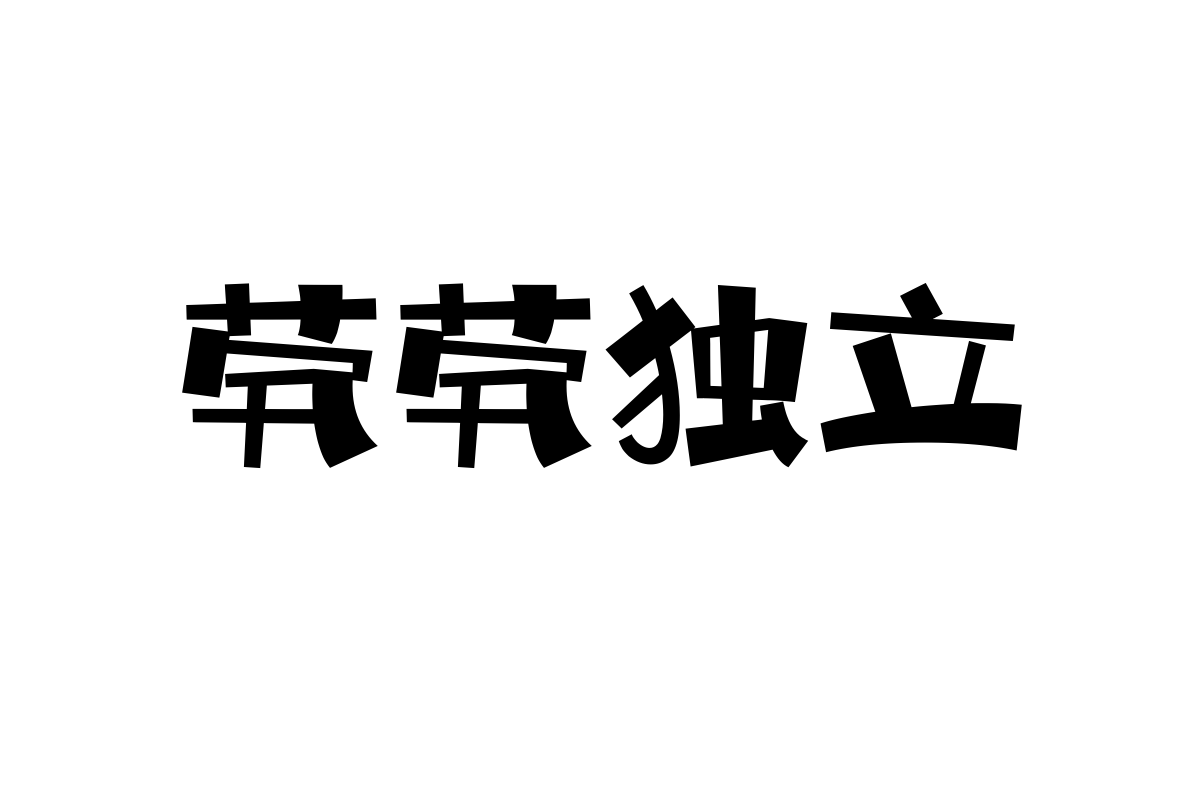
麦兜体是一种字体,它的字形独特,笔画流畅,给人一种轻松愉快的感觉。这种字体的特点是将麦兜这个角色的形象融入到了文字设计中,使得文字既有趣味性又不失正式感。
麦兜体的特点主要有以下几点:
1. 字形独特:麦兜体的字形不同于传统的宋体、黑体等标准字体,它有着独特的线条和形状,给人一种新颖的感觉。
2. 笔画流畅:麦兜体的笔画流畅,没有太多的停顿和顿挫,给人一种轻松愉快的感觉。
3. 易于识别:麦兜体的字形简单明了,一看就知道是什么字,这使得它在广告、宣传等领域得到了广泛的应用。
4. 适合儿童:由于麦兜体的特点,它非常适合用于儿童读物、儿童玩具等产品的设计,可以吸引孩子们的注意力。
总之,麦兜体是一种具有独特风格和特点的字体,它以其独特的字形、流畅的笔画和易于识别的特点,在各种场合得到了广泛应用。